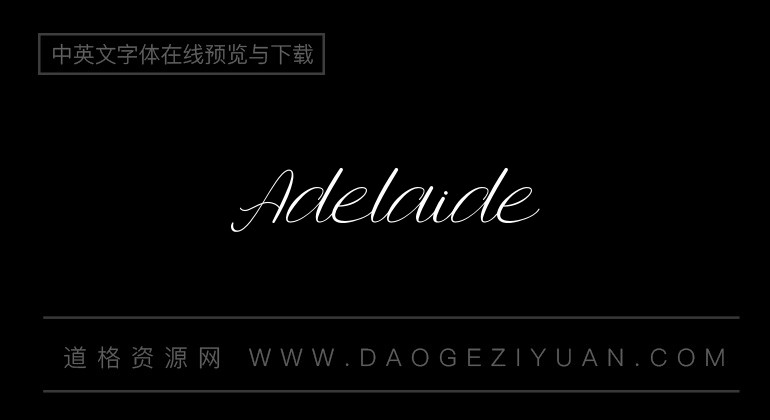
Adelaide
Adelaide 是一种清新、优雅的英文字体,它采用了细节丰富的线条结构,在字体中融入了传统古典风格的元素,使字体有着更加优雅的外观。Adelaide 字体具有较强的识别度,可以用于各种印刷品、网页设计、广告宣传等场景,让您的文字更加美观大方。
Adelaide是一款非常不错的手写艺术字体,具有很好的视觉感,适合于文化类的宣传设计、商业类品牌的广告和产品包装设计以及个性化文字排版等较多场景。